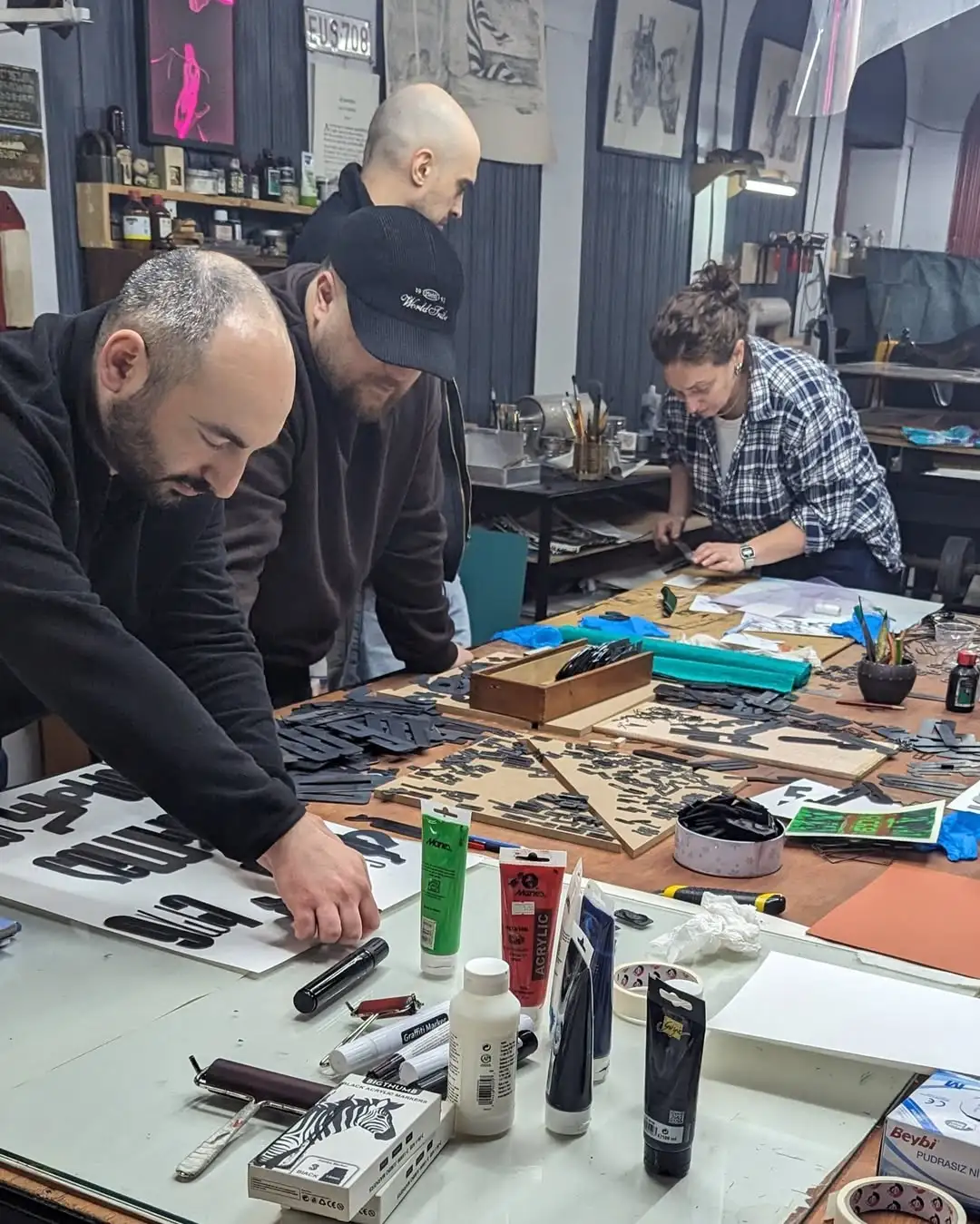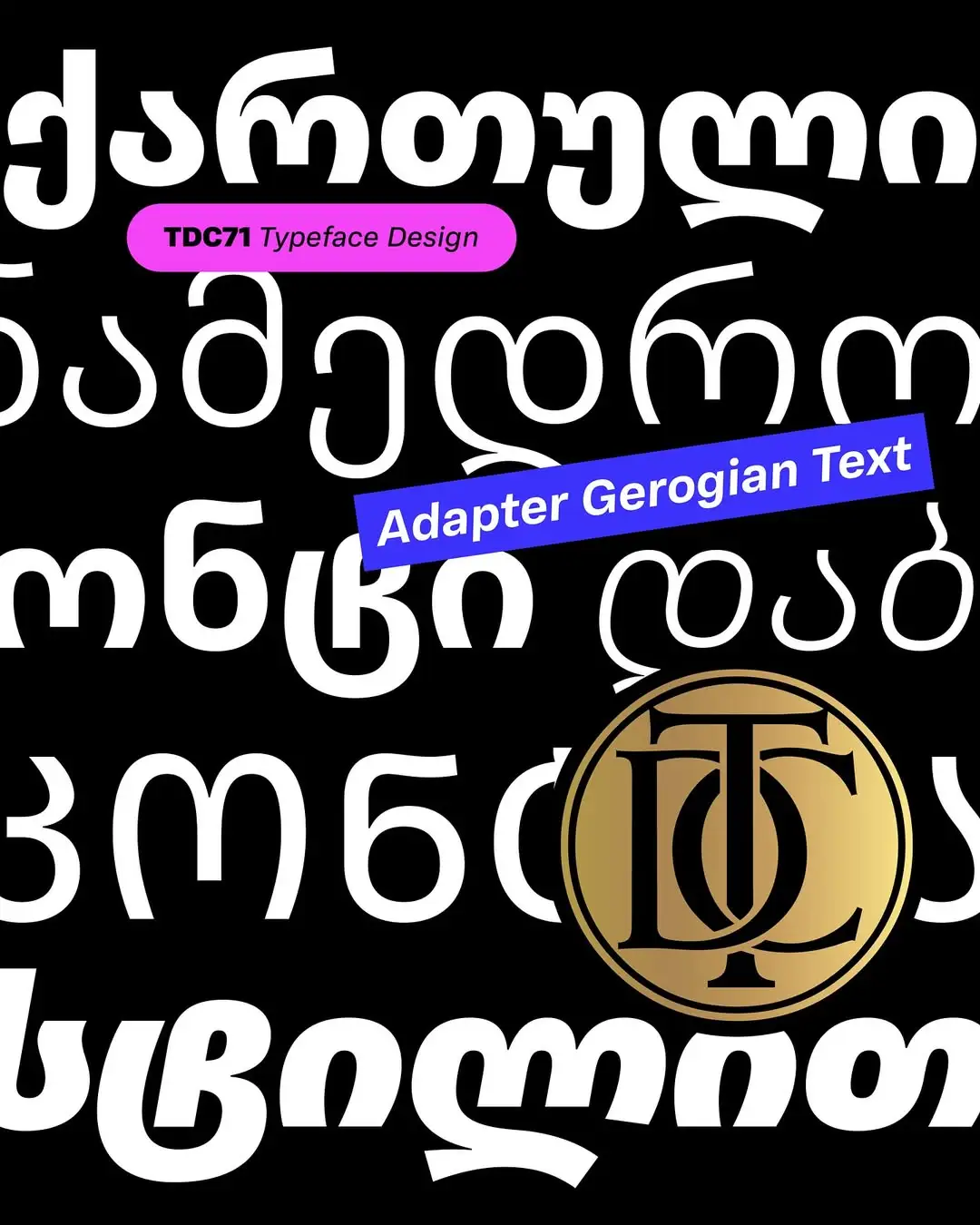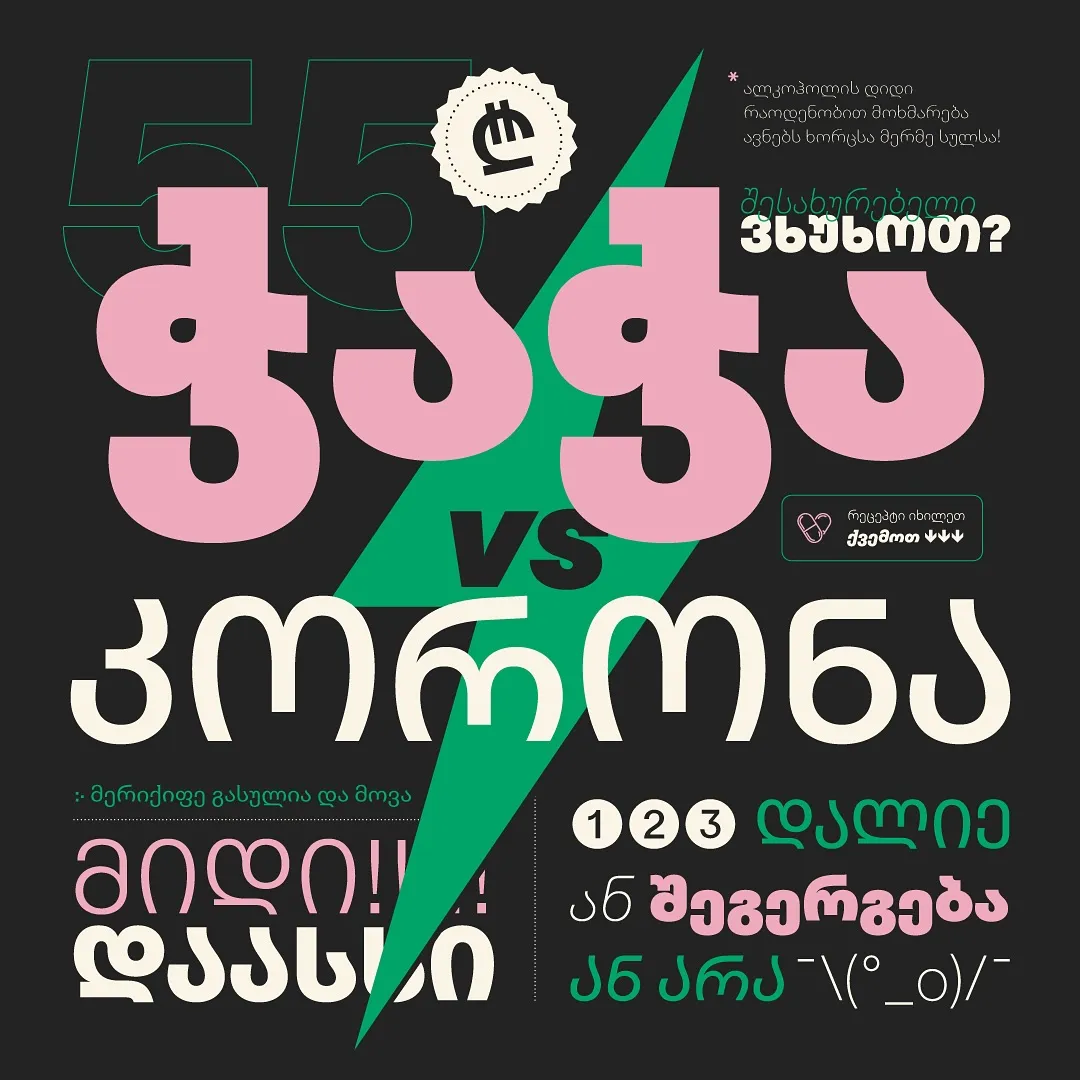
这里是亚洲和欧洲的交界,这里是中国古人熟悉的「阿蛮国」(《后汉书·西域传》)、「曲儿只」和「谷儿只」(《元史》),这里有着诸多神秘的文字,这是你地理和历史知识的盲区。经过多年策划与准备,我们将在今年五一假期期间,带你飞越中亚广阔的草原,走到亚洲最西的尽头,在格鲁吉亚和亚美尼亚高原,领略这片土地壮美的自然景观和历史悠久的文字谱系。
大高加索山脉东西绵延1200公里,横贯在黑海与里海之间,山势陡峻,海拔4800米以上山峰有15座,最高峰厄尔布鲁士峰海拔5642米,比勃朗峰高出近1000米。该地区主要国家有俄罗斯、格鲁吉亚、亚美尼亚和阿塞拜疆。
格鲁吉亚的历史最早可追溯到青铜器时代。亚美尼亚领土上最早的乌拉尔图王国在中国西周时期建立。公元4世纪初期的高加索地区,处在周边两大帝国的夹缝中——西边是信奉大公教的罗马帝国,东南边则是信奉索罗亚斯德教的波斯萨珊王朝,北面的斯拉夫人尚处在信仰本土多神教的小部落阶段。公元301年,亚美尼亚率先将基督教定为国教,是世界上第一个基督教国家。紧接着格鲁吉亚国王也将基督教尊为国教。到了中世纪,他们都经历了本土王朝的鼎盛时期,也遭受了蒙古、帖木儿、奥斯曼与波斯的轮番入侵。进入19世纪,两国都被沙俄吞并,在短暂独立之后,又被并入苏联,直到1991年苏联解体后恢复独立。
虽然格鲁吉亚和亚美尼亚在历史上有很多相似之处,但是两个国家的语言完全不同。前者属于南高加索语系,而后者属于印欧语系,在结构、词汇和书写系统上有着本质区别。在公元前 6 世纪的石刻中,我们就能发现使用楔形文字雕刻的亚美尼亚文。公元 405 年,曾经担任过宫廷秘书,熟悉多种语言的教士圣梅斯罗布·马什托茨(MesropMashtots)受亚美尼亚皇帝之命,经过了对希腊和闪米特等字母的研究,发明出了亚美尼亚字母。当时基督教在亚美尼亚已经作为国教存在了 100 多年。至于格鲁吉亚字母,虽然有传说也是由马什托茨发明的,但是也有别的说法,并没有确凿的历史记载。格鲁吉亚字母的出现晚于亚美尼亚字母,现存最早的实物来自公元 430 年。
DAY0(四月二十八日,第比利斯,格鲁吉亚)
到达格鲁吉亚首都第比利斯。
DAY1(四月二十九日,第比利斯,格鲁吉亚)
第比利斯的迷人之处在于传统建筑与苏联时期粗野主义建筑风格的对比与融合。在老城区,石砌的历史建筑与色彩斑斓的巴尔干风格阳台交相辉映,散发出悠久的历史和文化气息;而在市中心,粗犷而大胆的苏联时期建筑则以其简约的线条和功能主义设计给城市增添了现代感。这种传统与现代的碰撞,形成了第比利斯独特而多元的城市面貌,使其成为一个既保留历史韵味,又充满活力与创造力的文化中心。我们将住在第比利斯老城,这里有太多值得一看的地方。
圣三一教堂(Holy Trinity Cathedral)
也被称为格鲁吉亚圣三一教堂(Sameba Cathedral),是第比利斯的一座标志性宗教建筑,也是格鲁吉亚东正教的主要教堂之一,是格鲁吉亚最大最高的教堂。该教堂采用了典型的格鲁吉亚建筑风格,具有圆顶、尖顶、和细致的石雕装饰,整体现代而典雅,内部装饰华丽,拥有精美的马赛克、壁画和镀金的祭坛,展示了宗教艺术的精湛技艺和深厚的文化底蕴。教堂坐落在第比利斯的高地上,从那里可以俯瞰整个城市及其周围的自然美景,是游客和当地居民心目中的观光胜地。
格鲁吉亚编年史纪念碑(Chronicles of Georgia)
16根高达30多米的巨型青铜柱,犹如一个巨石阵。柱子上雕刻了从古代到现代的多个历史场景,包括古代王国、基督教的引入、以及格鲁吉亚人民的英雄事迹,反映了这个国家丰富的历史和文化身份。纪念碑像一个来自未来的考古遗迹,又像一部立体的教科书,沉默而磅礴。
安德罗波夫之耳(Andropovs Ears)
正式名称为“安德罗波夫特大楼”(Andropov Tower),因其形状和设计让人联想到耳朵而得名。该建筑建于1970年代,曾是苏联时期的一个秘密监控中心,主要用于监听并监视电信通信。今日的安德罗波夫之耳不仅作为历史遗址,也成为对冷战及其遗产反思的地方,象征着对自由和隐私权的思考。
旱桥市场(Dry Bridge Market)
是第比利斯最著名,最有人气的二手市场,也是外高加索地区最大的露天旧货市场。市场分成两部分,桥上以旧货、古董、苏联老物件为主,桥下则以油画、手工艺品为主。
DAY2(四月三十日,第比利斯,格鲁吉亚)
地下印刷所(Tbilisi Underground Printing House)
这是第比利斯的小众景点。1917年至1918年期间,斯大林曾经在这里工作,印刷和传播布尔什维克的宣传材料。地下印刷所成为了反对沙皇政权和后来苏维埃政权的重要基地。茅盾在其作品《子夜》中提到过第比利斯地下印刷所。1980年代,第比利斯地下印刷所开始秘密印刷反对苏联的印刷品,这一时期的印刷所成为了推动格鲁吉亚文化复兴和政治变革的重要力量。
格鲁吉亚字母印刷工作坊
我们将在当代图形中心(Graphic Contemporary Center)中体验各种印刷工艺,这里有石版、金属活字、塑料活字、金属活字片等各种印刷方式。我们也可以结合绘画、拼贴的手法创作出自己第一无二的作品。
格鲁吉亚字体设计工作坊
工作坊将由毕业于雷丁大学的字体设计师安娜·萨尼基泽(Ana Sanikidze)带来。
安娜·萨尼基泽是来自格鲁吉亚第比利斯的字体设计师和排版师。她于2021年毕业于雷丁大学的字体设计硕士项目。安娜是格鲁吉亚书法家协会的会员,她在格鲁吉亚公共事务研究所的视觉传播课程教授字体排印。她跟多家字体公司合作,开发格鲁吉亚字体,并获得过纽约TDC的字体大奖,是一位在国际领域非常活跃的格鲁吉亚设计师。
DAY3(五月一日,埃里温,亚美尼亚)
我们将包车从第比利斯前往亚美尼亚首都埃里温,一路上我们将领略高加索山脉壮美的自然风光,广阔的森林与静谧的湖泊,还有点缀期间的具有上百年历史的修道院和教堂。
沿途景点:
哈赫帕特修道院(Haghpat Monastery)
世界文化遗产,位于格鲁吉亚和亚美尼亚边境亚美尼亚一侧,修建于9世纪晚期,是典型的亚美尼亚建筑修道院建筑风格。修道院坐落在美丽的山谷中,四周环绕着壮观的高山和宁静的自然景观。
萨纳欣修道院(Sanahin Monastery)
世界文化遗产,毗邻哈赫帕特修道院,修道院内保存了丰富的艺术作品,包括壁画和雕塑。
迪利扬(Dilijan)
被誉为亚美尼亚的「小瑞士」,边上还有同名的国家公园,节奏松弛,生活气息浓厚,还有类似霍比特人的小房子。
塞凡湖(Lake Sevan)
被誉为「高加索之海」的塞凡湖占据了亚美尼亚国土面积近 1/6,是该国最大的湖泊,也是亚美尼亚最重要的自然景点之一。湖泊的海拔约为 1900 米,被群山环绕,景色十分壮观。附近还有亚美尼亚规模最大的诺拉图斯墓地(Noratus Cemetery),有超过 800 块十字石(khachkar),包含有大量宗教符号、花卉图案、十字架等。
DAY4(五月二日,埃里温,亚美尼亚)
Vernissage 周末市集
Vernissage 市集每周末举办,主要展示与销售当地的艺术与手工制品,摊主往往就是工匠本人,所以不仅可以买到富有特色的产品,还可以现场看到制作的过程。除此之外,市集上还经常能碰到传统音乐和舞蹈的表演,市集周边有很多其他文化景点与餐厅场所,是本地人和游客都爱去的社交中心。
埃里温大阶梯(Cascade Complex)
这是最能代表埃里温城市气质的公共建筑。它既是贯通上城与下城的通道,也是跨越苏联时代和独立后的亚美尼亚的城市地标。大阶梯的设计始于1970年代,完工于2009年,以其巨型尺度和粗野主义建筑风格让人过目不忘。站在台阶的顶端可以俯瞰埃里温市全景,这里早已没有了领袖雕像和口号,取而代之的是一种深沉和静谧,默默映衬着远方亚美尼亚人的神山阿拉拉特山,那是传说中诺亚方舟最后停泊的地方。
共和广场 & 国家博物馆(National Gallery of Armenia)
共和广场是埃里温的主要广场,也是亚美尼亚首都最知名的标志之一。该广场创建于1926年,是该市大型重建计划的一部分,由著名建筑师亚历山大·塔马尼安设计。几十年来,直到1991年,它被称为列宁广场,反映了亚美尼亚的苏联过去。今天,它是亚美尼亚身份、历史和建筑优雅的生动体现。
亚美尼亚国家美术馆坐落在首都埃里温共和国广场的一座八层大楼里面,这座大楼是首都的最知名的地标之一。国家美术馆只占有大楼的三到八层,最底下的两层是亚美尼亚历史博物馆(History Museum of Armenia)。展馆内珍藏了大量与亚美尼亚历史、文化和社会发展的相关文物。藏品超过 4 万件,包括考古发现、手工艺品、艺术作品以及与亚美尼亚历史相关的文献和文物。藏品覆盖了从公元前的古代文明到现代历史的各个时期。亚美尼亚历史博物馆是理解和探索亚美尼亚历史的绝佳场所。博物馆所在的共和广场也是埃里温的中心广场,晚上还有喷泉表演。
亚美尼亚种族灭绝纪念馆(Genocide Memorial)
第一次世界大战期间,尤其在 1915 至 1923 年间,150 万亚美尼亚人遭受种族灭绝。纪念馆不仅是对历史的反思,也是对亚美尼亚文化和人道主义的深刻致敬。纪念馆的标志性建筑是一个高耸的仿圆顶纪念碑,象征着对被害者的悼念。它的设计简洁而庄重,象征着希望和坚韧。纪念馆前面有一个广阔的墓地,葬有为捍卫亚美尼亚权益而牺牲的人们。这些墓碑和花圈体现了人们对逝者的敬仰和缅怀。
DAY5(五月三日,埃里温,亚美尼亚)
手抄本博物馆(Matenadaran)
成立于1959年,是亚美尼亚十分重要的文化与学术机构。博物馆收藏了超过4万件手抄本和文件,包括历史、文学、哲学、医学等领域的作品,其中许多是极为珍贵的历史文献。
Matenadaran不仅是一个博物馆,还是一个研究机构。它提供研究机会,推动亚美尼亚语言和文化的研究,同时也专注于手稿的保护和修复工作。
亚美尼亚字体工作坊
我们将邀请同样毕业于雷丁大学的字体设计师格尔·字翰扬(Gor Jihanian)带来亚美尼亚字体设计工作坊。格尔是一位具有国际影响力的亚美尼亚字体设计师,他曾与 TPTQ、TypeTogether、Dinamo 等多家著名字体公司合作开发亚美尼亚字体,也因此获得纽约 TDC、Granshan 等字体大奖。多年前他举家从美国回到祖国亚美尼亚,开始更为深入地研究亚美尼亚的字体历史与文化。他收藏了大量苏联时期的书籍封面美术字,也做过详尽的埃里温街头招牌记录。在他的工作室,还有神秘的印刷材料和设备可以体验!除了工作坊之外,他也将在埃里温陪同我们一起漫步和参观。
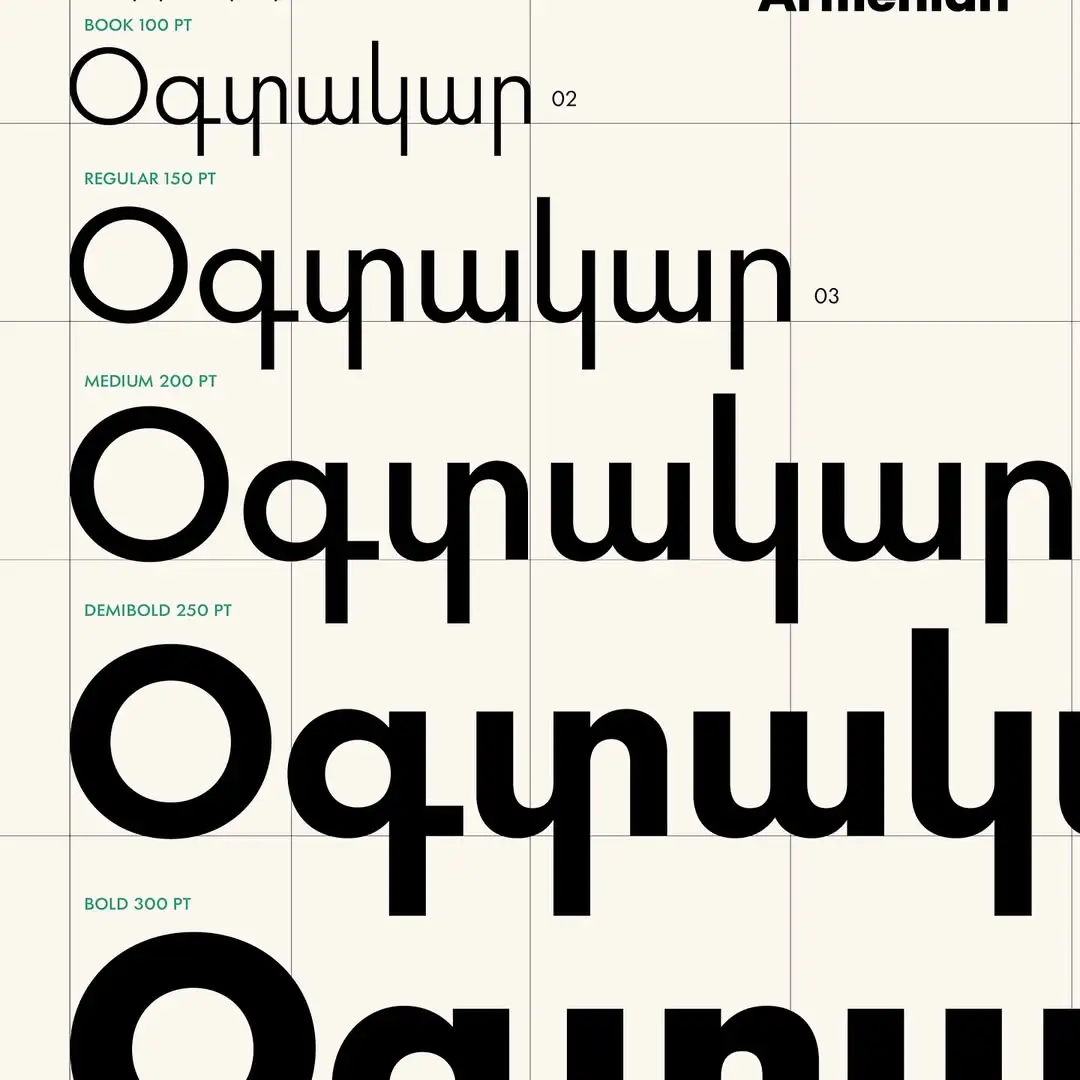
亚美尼亚字母是公元5世纪时候依据希腊字母和闪米特字母发明的,距今已经有 1621 年历史。亚美尼亚字母一共有 38 个,区分大写与小写。最有意思的是亚美尼亚文的标点符号,所有的句子结尾都是类似冒号的两点,而如果是疑问句或感叹句,会有特殊的上标符号添加在某一个单词的上面!我们将使用自己在街头漫步、博物馆参观时收集到的亚美尼亚字体照片,结合 Gor 海量的收藏,用一个下午的时间尝试设计一套亚美尼亚字体。